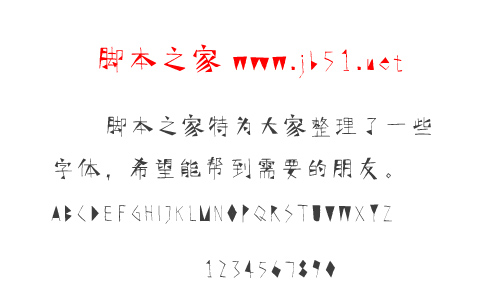
漢儀柏京體簡字體是一款非常別具一格的簡體中文字體,字體風格活力蓬勃,筆勢伸展如龍蛇舞動,同時又受歐陽體的影響,結(jié)構(gòu)布局是平正工整,嚴謹峭勁,有疏有密,穩(wěn)中而生動。漢儀柏京體技術(shù)上借鑒了歐式傳統(tǒng)鋼筆的剛勁筆鋒, 三角形和線條的組合產(chǎn)生了表現(xiàn)主義的豪放效果??梢詰?yīng)用于廣告設(shè)計、名片設(shè)計、包裝印刷、產(chǎn)品設(shè)計等應(yīng)用。歡迎有需要此款字體的朋友們前來下載使用。